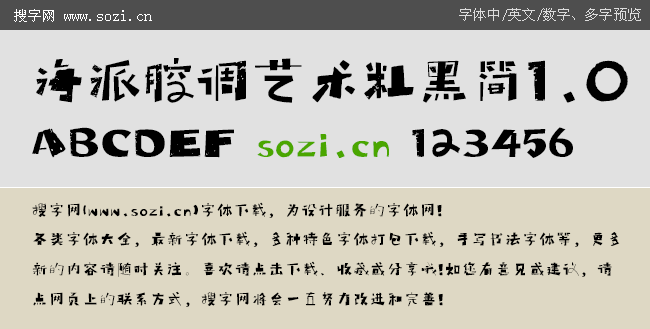
海派腔調(diào)藝術(shù)粗黑簡1.0
搜字網(wǎng)提供一海派腔調(diào)藝術(shù)粗黑簡1.0中文字體下載,海派腔調(diào)藝術(shù)粗黑簡字體是一款左粗右細、整體效果非常出眾的簡體中文字體,適合應(yīng)用于廣告設(shè)計、名片設(shè)計、包裝印刷、產(chǎn)品設(shè)計等應(yīng)用。